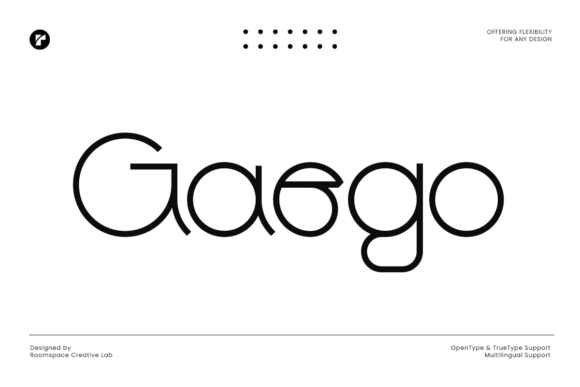
Gaego
適切なデザイン要素を見つけるのは難しい場合がありますが、Gaegoは作品を即座に引き立てる優れたコレクションを提供します。
精密に作られたGaegoは、クリーンなベクター、滑らかなタイポグラフィ、そして安心のための商用ライセンスを提供します。
POD(オンデマンド印刷)製品、結婚式の招待状、またはソーシャルメディアのグラフィックを作成している場合でも、Gaegoは理想的です。